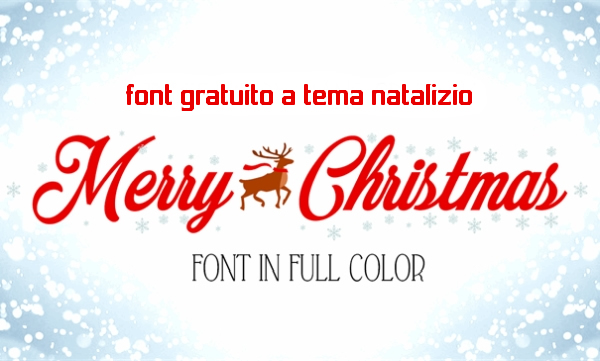
A Natale per creare cartoline, lettere o post da pubblicare sui social, è meglio avere nella propria raccolta di fonts qualche carattere di testo a tema.
A questo proposito vi segnalo, sul sito Font Space, un bel carattere di testo con tema il Natale.
Merry Christmas Color Font | font gratuito a tema natalizio